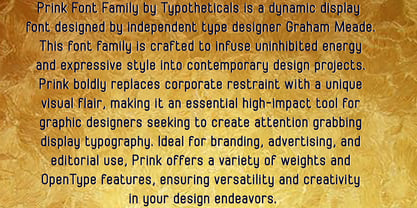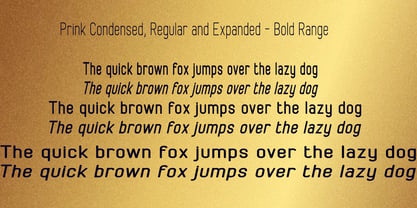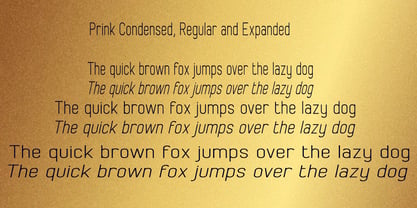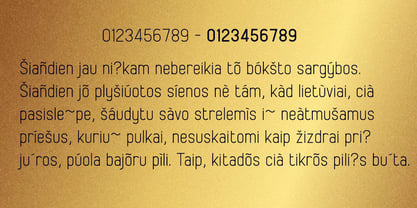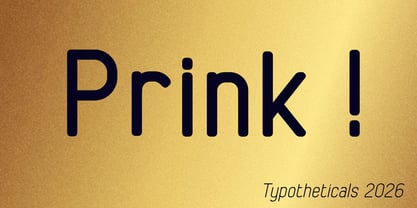
Prink
por Typotheticals
La familia tipográfica Prink fue diseñada por Graham Meade y publicada por Typotheticals. Prink contiene 12 estilos y opciones de paquete familiar. Más información sobre esta familia
Prink Font Family by Typotheticals is a dynamic display font designed by independent type designer Graham Meade. This font family is crafted to infuse uninhibited energy and expressive style into contemporary design projects. Prink boldly replaces corporate restraint with a unique visual flair, making it an essential high-impact tool for graphic designers seeking to create attention-grabbing display typography. Ideal for branding, advertising, and editorial use, Prink offers a variety of weights and OpenType features, ensuring versatility and creativity in your design endeavors.
Diseñadores: Graham Meade
Fundición: Typotheticals